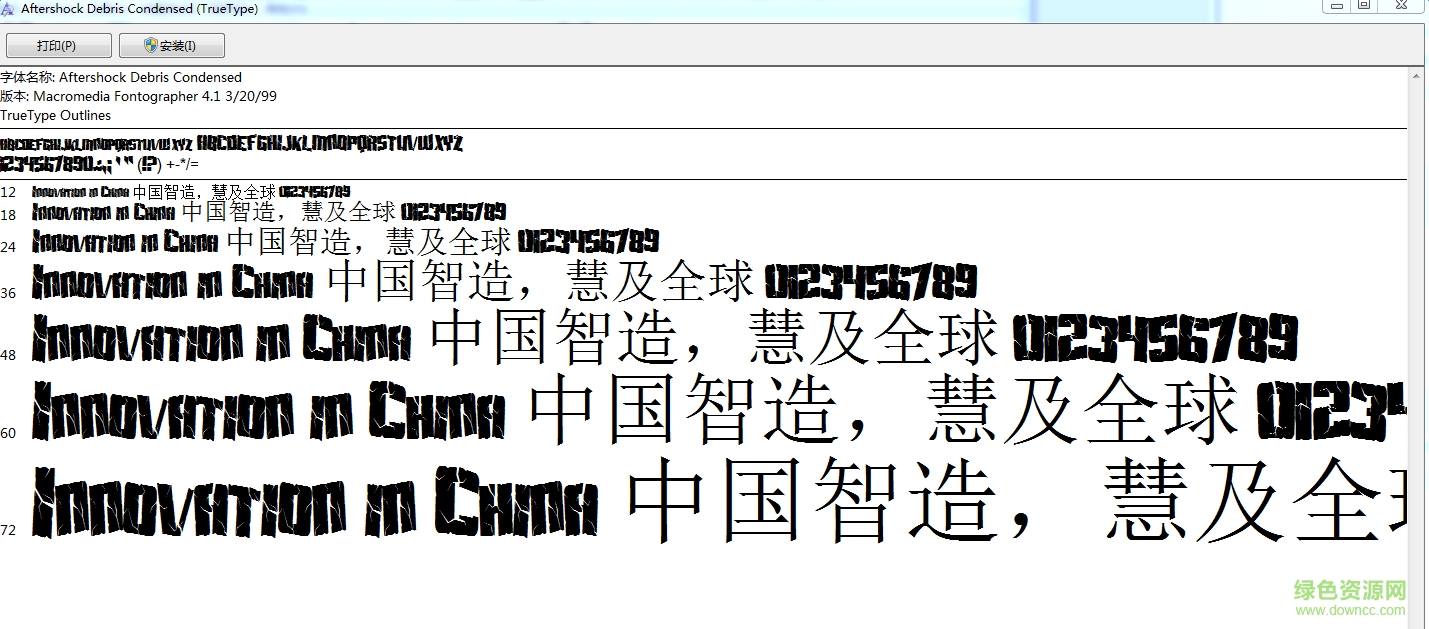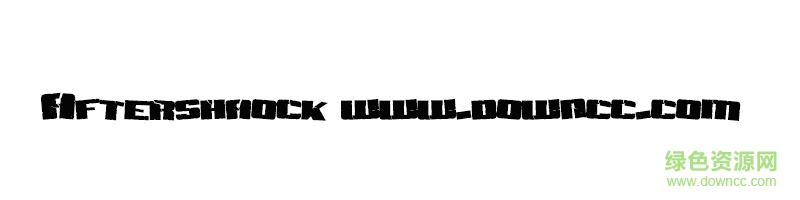
Aftershaock字體是一款A(yù)ftershaock風(fēng)格英文字體軟件,Aftershaock風(fēng)格的字體給人非??褚暗母杏X,深受廣大年輕人的喜愛,還有更多好看字體盡情期待,歡迎到綠色資源網(wǎng)下載體驗(yàn)!
Aftershaock是一款A(yù)ftershaock風(fēng)格英文字體,字體效果比較狂野,喜歡英文體字的朋友可以下載使用看看效果如何。